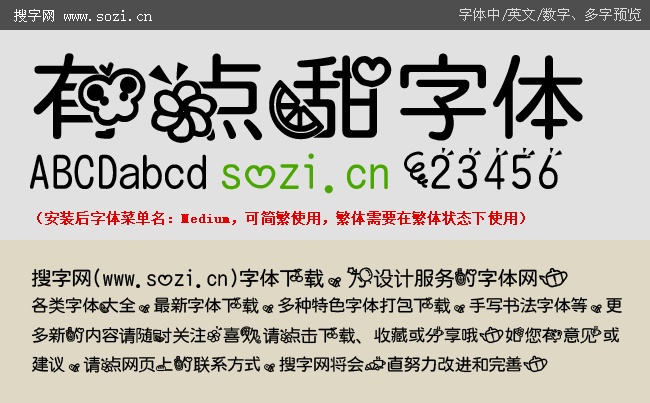
有點(diǎn)甜字體
搜字網(wǎng)給大家提供一款有點(diǎn)甜字體手機(jī)中文字體下載。這款手機(jī)字體是以圓體字體為原形,筆畫間嵌入了大量可愛的卡通圖案。在具備圓字體清晰端正的風(fēng)格同時(shí),卡通味也特別濃,是一款非常可愛的卡通字體,特別適合喜歡手機(jī)字體個(gè)性一些的朋友在手機(jī)上安裝使用。